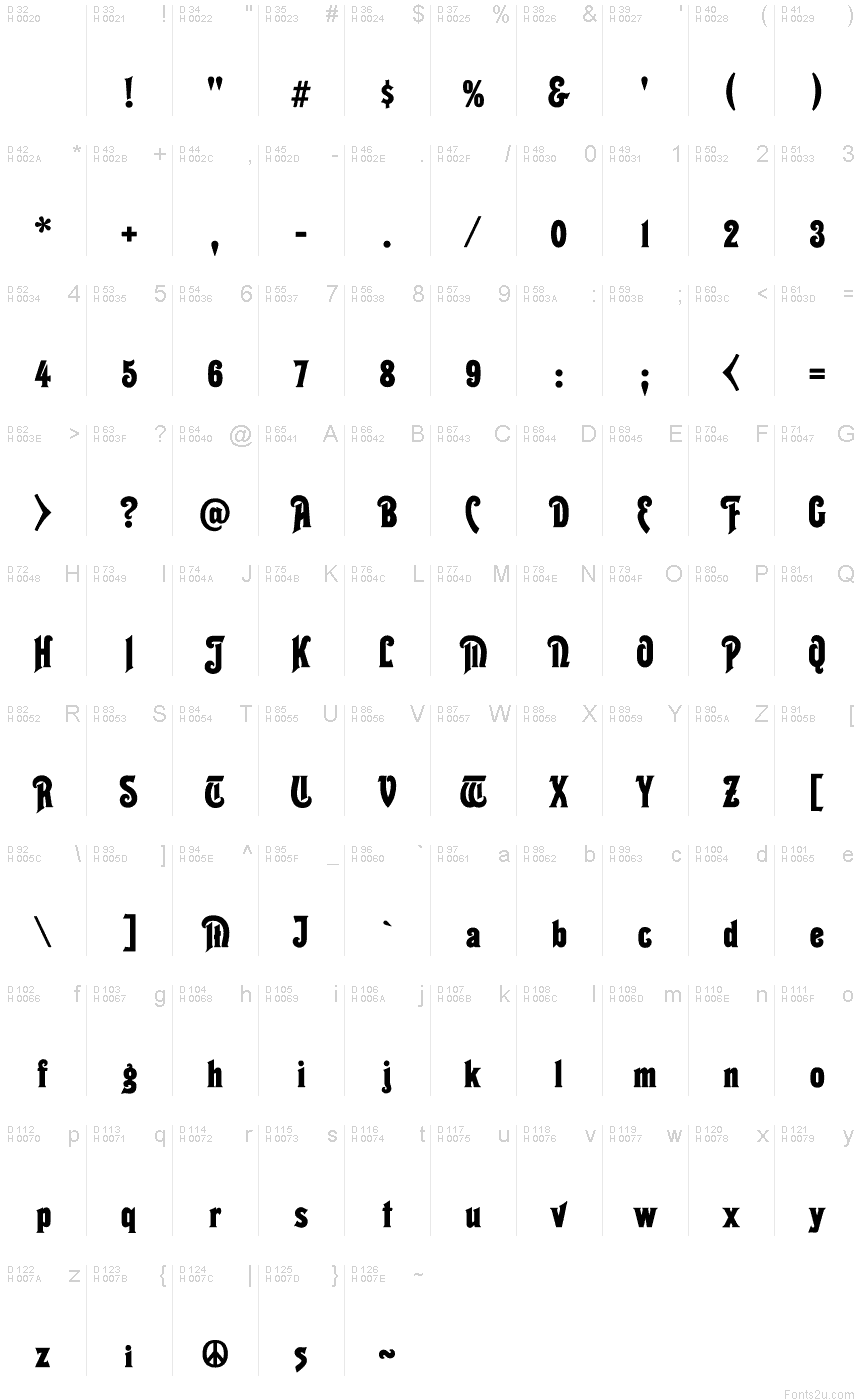
Thaleia
Thaleia، هو خط عرض (display font) مجاني بنمط blackletter من تصميم هارولد لونر، ينقل أجواءً مسرحية من العالم القديم من خلال ضربات عريضة تبدو وكأنها منحوتة وحروف ثقيلة ومنحنية. تبدو الحروف متجذرة في فن الخط في العصور الوسطى، مع قمم تشبه الإسفين، وأقواس عميقة، ومنعطفات داخلية مستديرة تحافظ على ملمس جريء بدلاً من أن يكون متكلفاً.
إنه مناسب لعناوين الملصقات، وأغلفة الكتب، وهويات الحانات والمهرجانات، وتغليف المنتجات الموسيقية، وبطاقات العناوين حيث تحتاج اللمسة التاريخية إلى ثقل حقيقي. وبكونه خطاً مجانياً، يعمل Thaleia أيضاً بشكل جيد مع الحروف المتداخلة (monograms)، ومستهلات الفصول، وشعارات الكلمات القصيرة، لأن تلك الأشكال الكثيفة والمنحوتة تجلب الأجواء بسرعة حتى في بضع كلمات فقط.